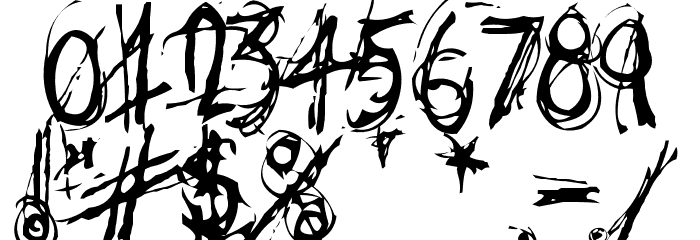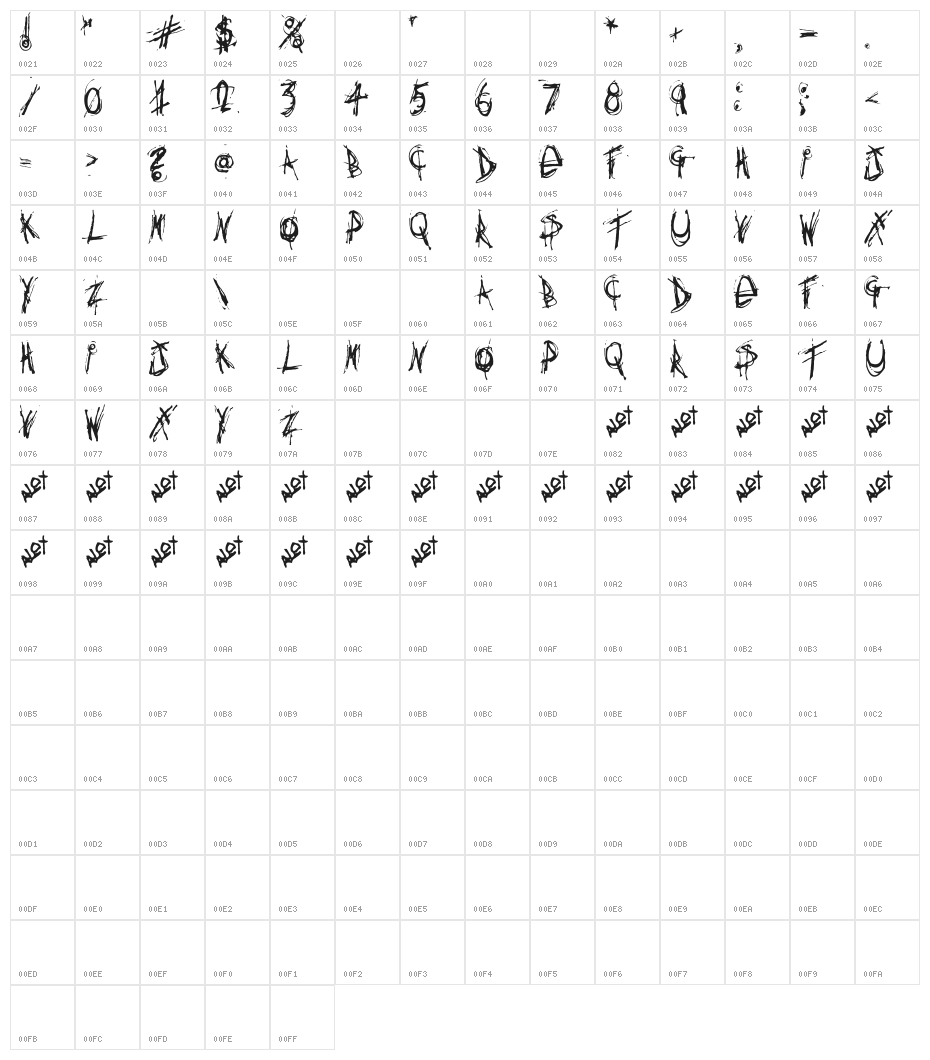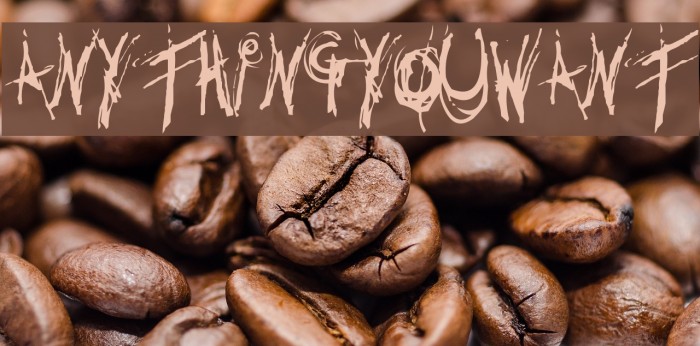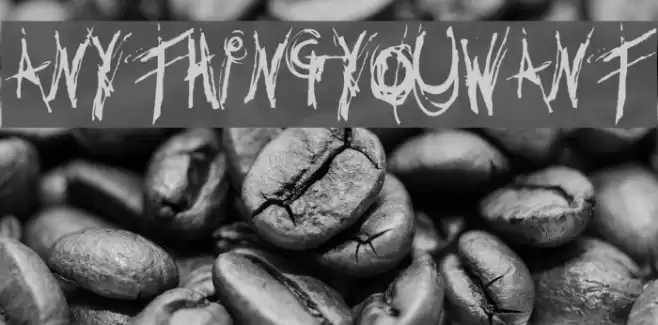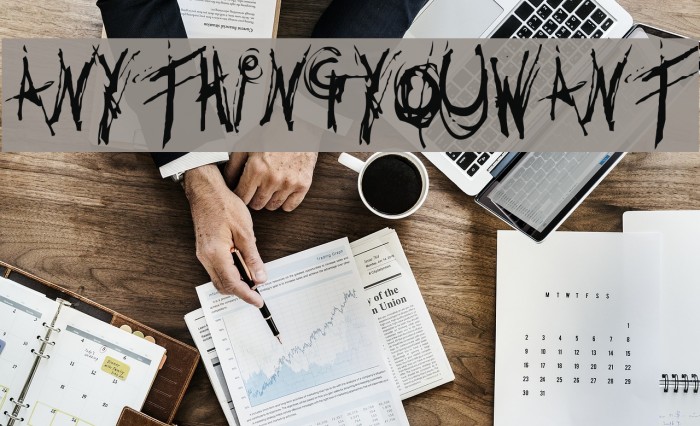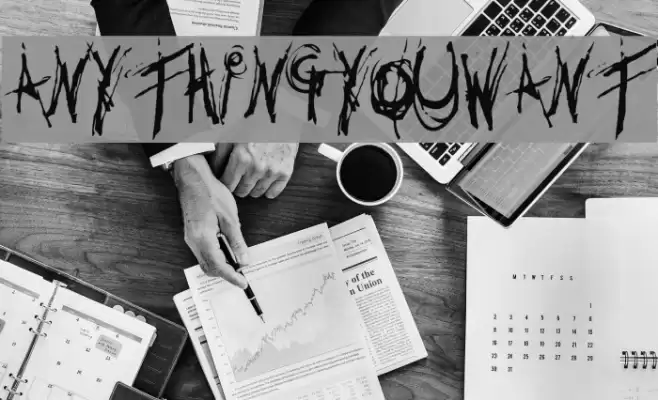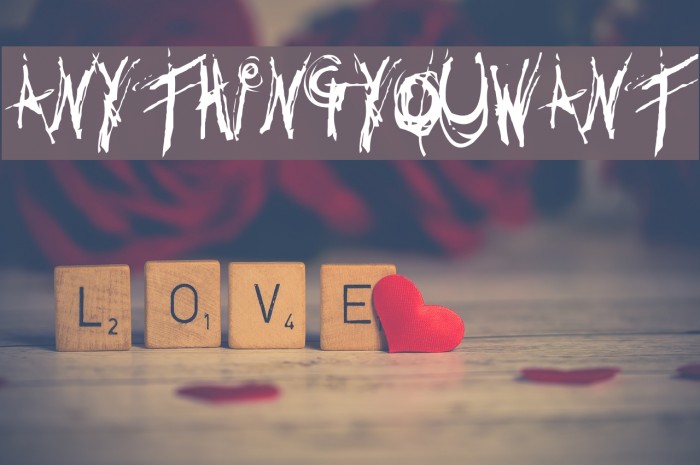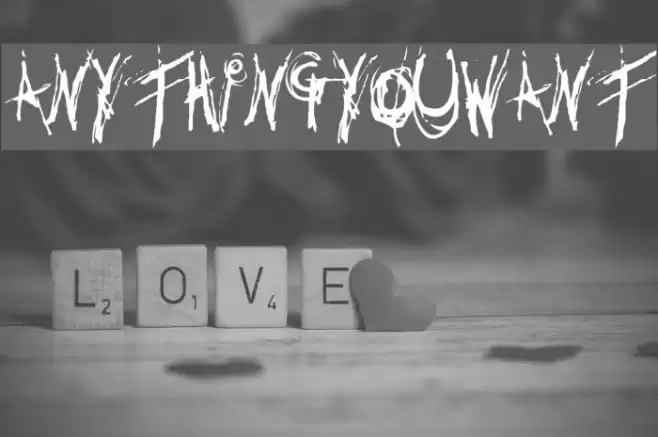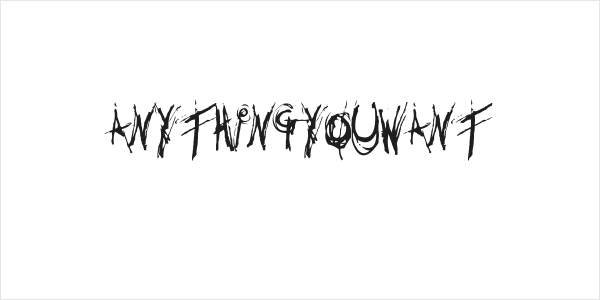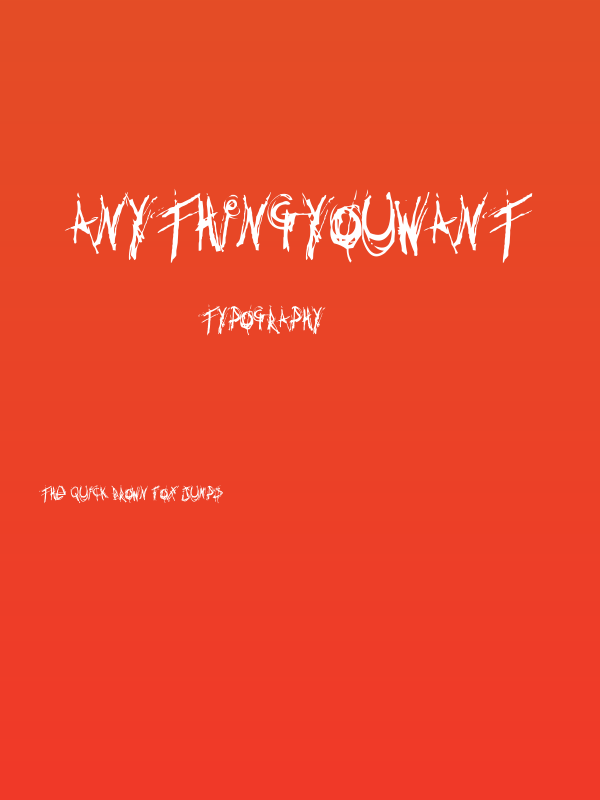
Anythingyouwant Font
| 全体的なスタイル | Grunge, Edgy |
| おすすめプロジェクト | Ideal for music album covers, edgy posters, streetwear branding, or any project needing a rebellious touch. |